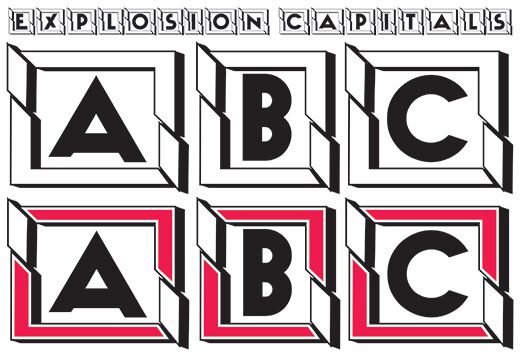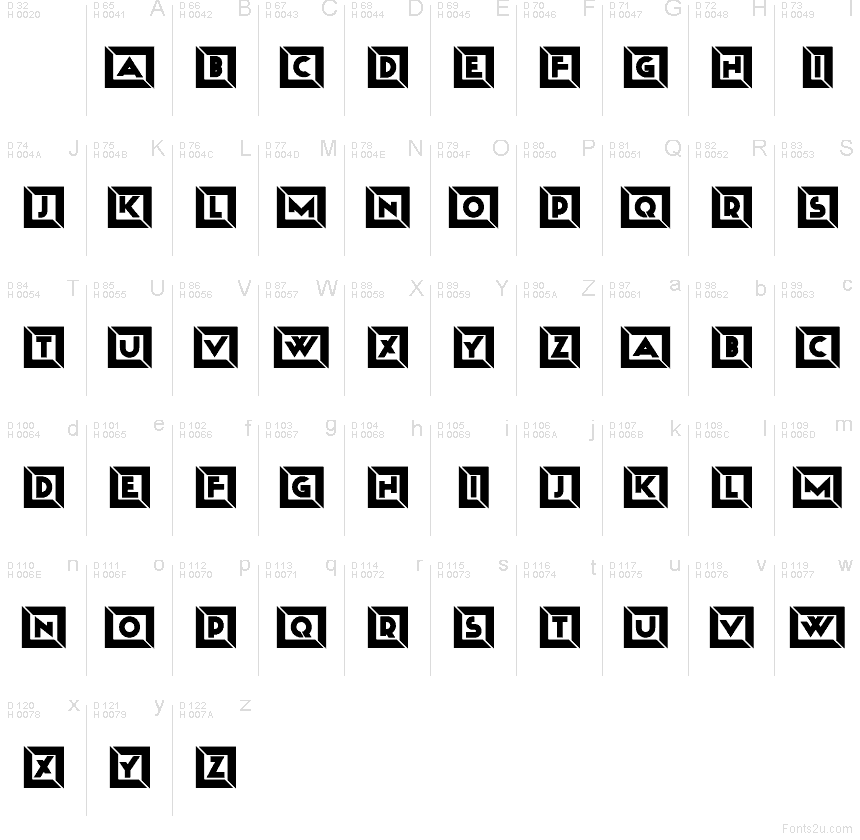
Explosion Capitals Extravagant Regular
Explosion Capitals Extravagant von Vladimir Nikolic ist eine kostenlose geometrische Display-Schrift in Box-Optik, die den lauten Stil der Poster-Ära einfängt. Die Großbuchstaben sind in quadratische Panels eingebettet, die an abgeschrägte Fliesen oder flache 3D-Schilder erinnern. Eine Kombination aus wuchtigen Blockformen, diagonalen Schnitten und kreisförmigen Öffnungen sorgt für einen prägnanten, grafischen Rhythmus.
Durch diese Rahmung ist die Schrift die erste Wahl für Albumcover, Event-Poster, Arcade-Titelkarten, Streetwear-Designs und markante Monogramme, bei denen die Buchstaben fast wie Embleme wirken. Als kostenloser Font eignet sie sich hervorragend für kurze Headlines und Cover-Texte, da jedes Zeichen bereits mit einem fertigen Rahmen und einer integrierten Tiefenwirkung geliefert wird.
Kombinieren Sie kleine und große Buchstaben für beeindruckende Ergebnisse!